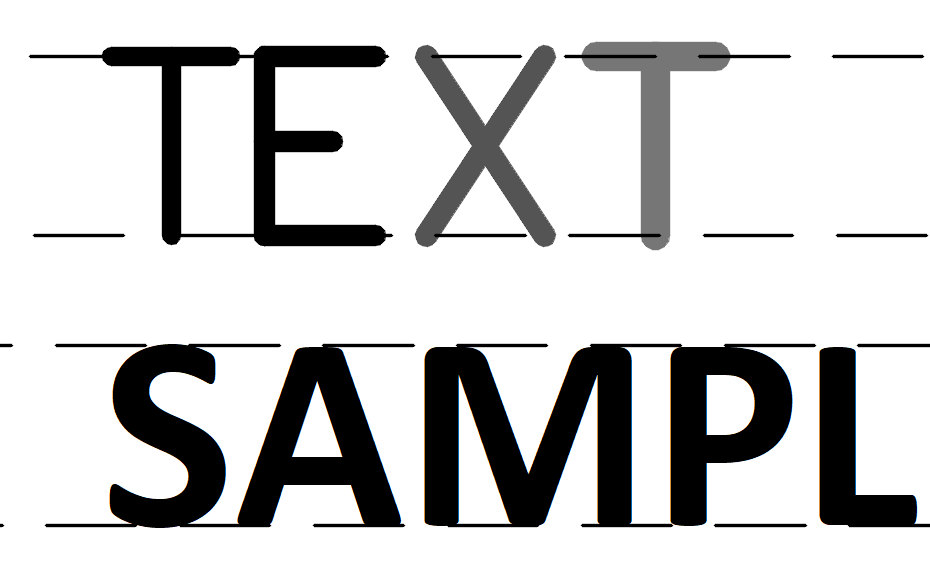
Font SHX là gì? Tầm quan trọng trong bản vẽ kỹ thuật AutoCAD
Khác với các phông chữ TrueType (.ttf) hay OpenType (.otf) dùng trong thiết kế đồ họa thông thường, định dạng .shx được tối ưu hóa đặc biệt cho các phần mềm CAD của Autodesk.
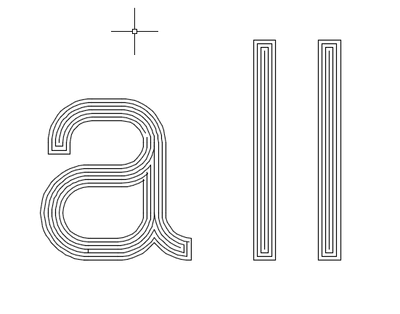
Định dạng Shape Font (.shx) chuyên dụng cho CAD
Đặc trưng lớn nhất của Font SHX là được xây dựng dưới dạng các tập hợp hình học vector (shapes) thay vì đường cong phông chữ tiêu chuẩn. Điều này giúp phần mềm AutoCAD render văn bản cực kỳ nhanh chóng ngay cả trên những bản vẽ hàng nghìn chi tiết phức tạp mà không làm nặng tệp tin. Các đường nét của font SHX luôn giữ được độ sắc nét hoàn hảo khi phóng to, thu nhỏ hay xuất bản vẽ sang định dạng PDF kỹ thuật.
Giải mã các dòng font SHX phổ biến tại Việt Nam
- VNSimple SHX & VNSimli SHX: Các bộ phông chữ quốc dân hỗ trợ gõ tiếng Việt trong AutoCAD theo các bảng mã cũ (như TCVN3 hoặc VNI), giúp hiển thị chính xác các chú thích bản vẽ mặt bằng, kết cấu.
- 3T Unicode SHX: Phiên bản nâng cấp hỗ trợ bảng mã Unicode hiện đại, giúp việc trao đổi bản vẽ giữa các đơn vị tư vấn thiết kế và nhà thầu diễn ra mượt mà, không bị xung đột mã nguồn.
- Ứng dụng thiết kế sáng tạo: Ngoài bản vẽ kỹ thuật, nhiều designer còn sử dụng phông chữ SHX để tạo ra các thiết kế bao bì mang phong cách “Blueprint” (bản vẽ kỹ thuật công nghiệp) vô cùng độc đáo.
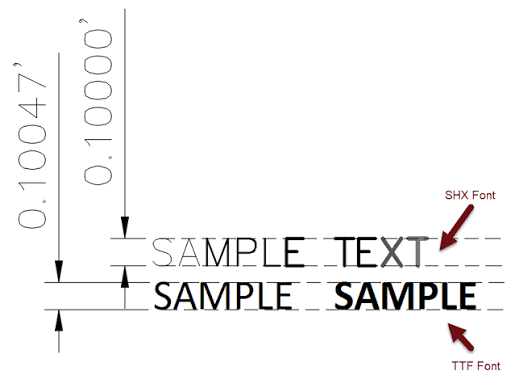
Phong cách bản vẽ kỹ thuật (Blueprint aesthetic) từ định dạng SHX đã vượt ra ngoài ranh giới xây dựng để trở thành một nguồn cảm hứng sáng tạo trong ngành bao bì:
- Tem nhãn thông số kỹ thuật: Các ký tự hình học gọn gàng giúp tem dán thông số trên các kiện hàng công nghiệp dễ tra cứu và mang tính thẩm mỹ cao.
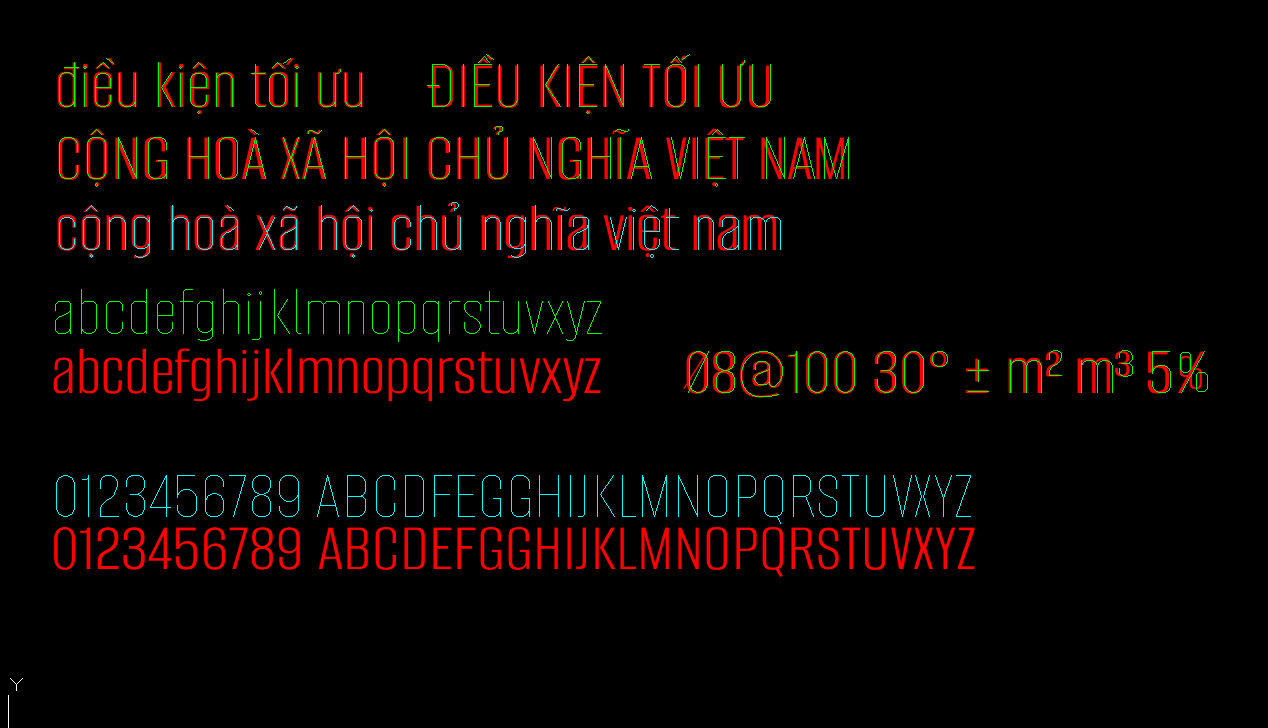
Lưu ý kỹ thuật khi sử dụng bản vẽ CAD để đưa vào in ấn bao bì
Nếu bạn muốn chuyển đổi các bản vẽ kỹ thuật từ AutoCAD sang các phần mềm đồ họa như Adobe Illustrator để sản xuất bao bì tại Doozypack.vn, hãy lưu ý: